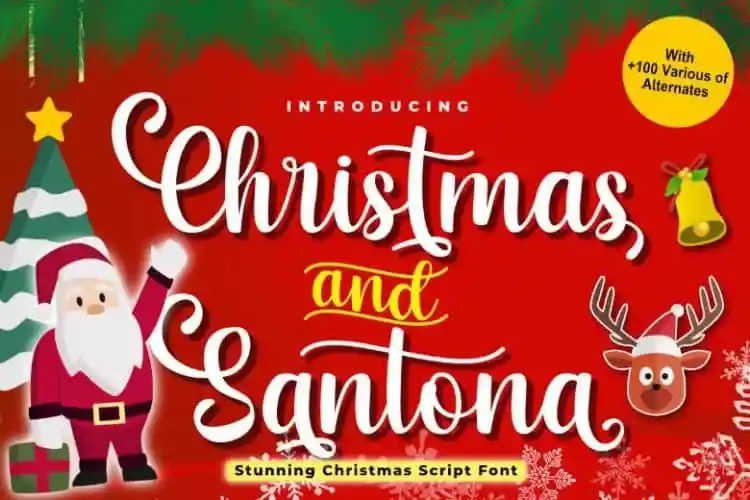
Christmas And Santona Script Font – Download Grátis
A fonte “Christmas And Santona Script Font” é uma escolha perfeita para aqueles que desejam adicionar um toque especial a suas criações no período natalino, seja em cartões de agradecimento ou em qualquer projeto de crafts com um ar romântico. Desenvolvida pela Andrimada Creative, esta fonte é uma alegre escrita à mão que transmite felicidade e diversão. Ideal para personalizar seus designs natalinos, especialmente quando o tema é festas de final de ano ou presentes carinhosamente feitos com a mão. Seja para um belo cartão natalino ou para decorar uma peça de crafts delicadamente detalhada, esta fonte traz um toque de encanto à sua criação. Fique por dentro dos recursos gráficos e descubra como tornar ainda mais especial seus projetos nesse período cheio de celebrações.